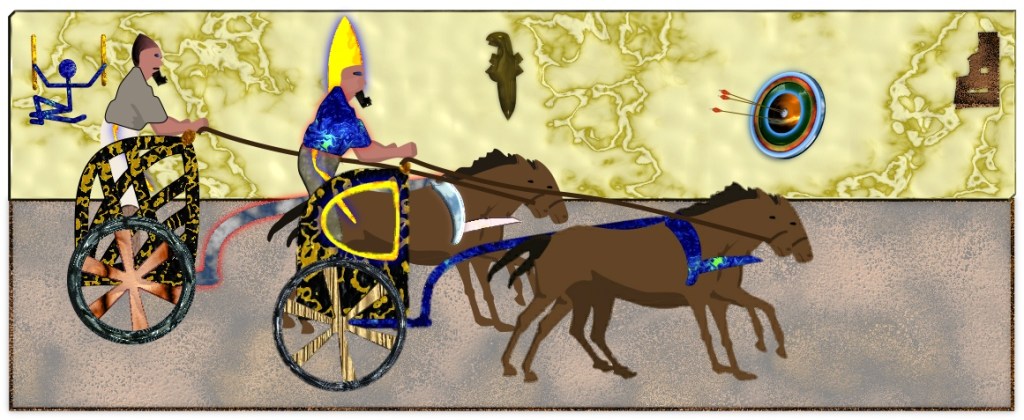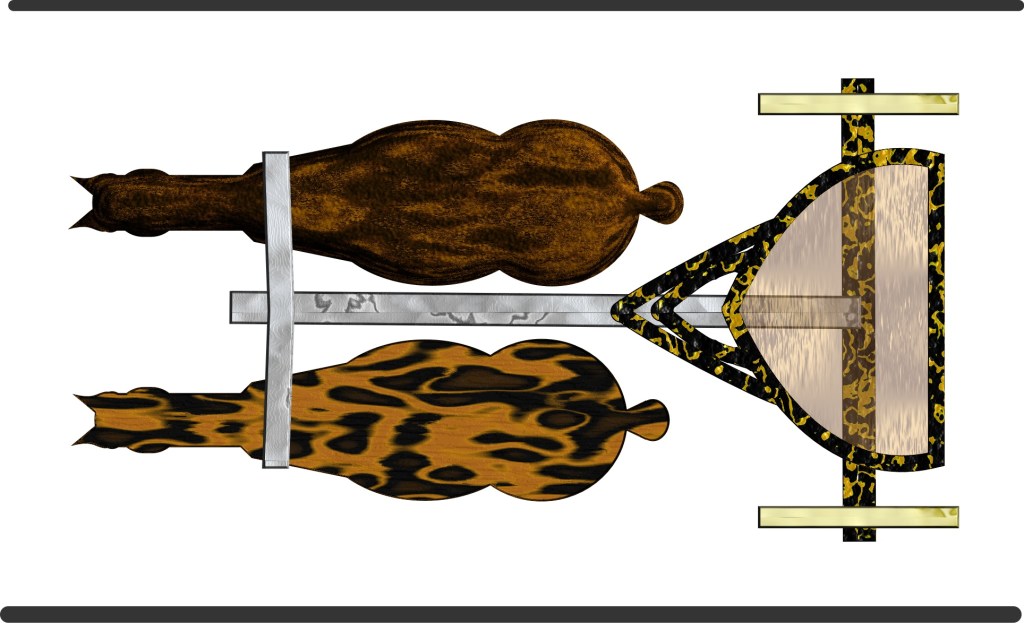
L’Étonnante Marelle Antique.
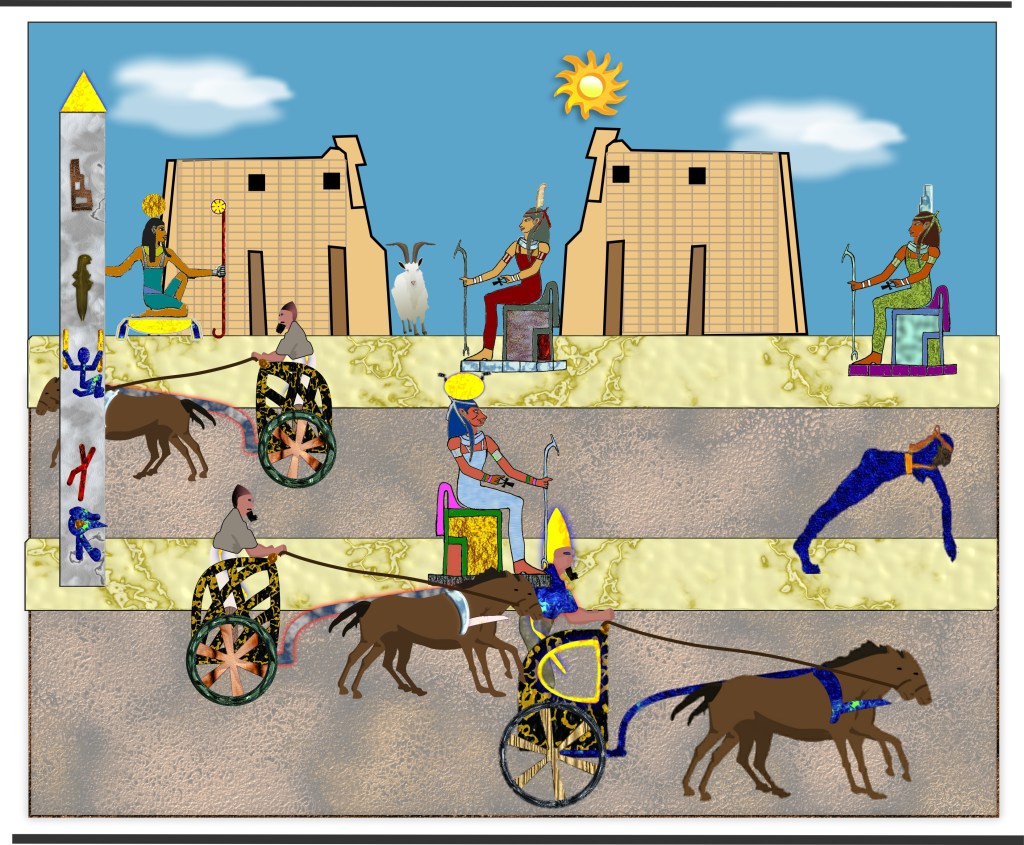
Une fois que l’on associe les signes hiéroglyphiques avec leurs propriétaires divins, il devient possible de les placer en fonction de ce que la marelle équestre nous propose.
Sa forme et ses dispositions prennent du sens car elle exprime clairement les croyances fondamentales Égyptienne, désigne ses personnages principaux et raconte aussi leurs rôles et interactions.
Sans marelle nous avons une simple liste de signes pratiques, avec elle nous avons un mode d’emploi et nous pouvons en admirer la cohérence. Encore plus étonnant, le manège équestre contemporain incorpore la quasi-totalité des ancêtres des lettres qu’utilisent quotidiennement des milliards d’humains.
Et il faut reconnaître qu’aucune autre explication de sa disposition ne répond totalement aux questions que nous nous posions au début de l’enquête.
La double finalité d’outil de formation et de lieu spirituel répond à la question de base : qu’est-ce que c’est ?
Ce n’est qu’un début. Le manège équestre Égyptien nous pose encore quelques questions : pourquoi l’avoir créé, qui l’a commis, quand le pensa-t-on et enfin où a-t-il été réalisé ?
Ce que nous recherchons, à défaut d’une nomenclature des constructions remarquables nous indiquant « ici l’on trouve le premier manège équestre de la nième dynastie », est un faisceau de présomptions mêlant les besoins, les capacités et les qualifications nécessaires, pendant une période de quelques centaines d’années.
C’est donc par une analyse des besoins que nous pouvons commencer, sachant que le manège est contemporain à l’introduction des chevaux en Égypte et forcément antérieur à la reconquête de l’ensemble de son territoire.
La Puissance du Sud.
Les suspects sont tout trouvés : comme créateurs d’une vaste école de cavalerie, les Antes, famille royale de la Haute-Égypte de l’époque dite du Nouvel Empire ont tout pour nous plaire.
Ils composent une lignée nombreuse, guerrière, volontaire et surtout Pharaonique. Historiquement, elle marque la fin de la 17e puis le commencement de la 18e dynastie suivant une continuité exceptionnelle, les changements de numérotation induisant normalement la disparition d’une famille au bénéfice de la suivante.
Ses personnages les plus éminents sont des Pharaons successifs : le grand-père Senakhtenrê Lâhmes, le père Seqenenrê Tâa et ses fils Khamôsis et Ahmôsis 1er, déjà cité comme étant le premier Pharaon « équestre » illustré.
A eux tous, ils forment la lignée des combattants ayant réuni la Haute et la Basse Égypte, en se battant longue-ment contre les Hyksôs, ces usurpateurs cavaliers qui s’étaient emparés de la Basse-Egypte près d’un siècle plus tôt.
Cependant, si ces rois sont importants, leurs reines le sont encore plus, qu’il s’agisse de la grand-mère Tétishéri, d’extraction de basse aristocratie, de sa fille Iahotep, qui épouse son frère Seqenenrê Tâa et de la petite fille Nefertary l’une des sœurs qu’épouse Ahmôsis.
Elles sont, chacune d’entre elles, extraordinaires de par leurs influences comme sœurs, épouses, régentes et souveraines successives.
Cela se remarque d’ailleurs dans les titres et honneurs qui leur sont attribués autant de leur vivant qu’après : reines, épouses royales, grandes épouses royales et enfin épouse de dieu , le grade le plus élevé à ce jour.
La grand-mère, la fille et la petite fille bénéficient de du-rées de vies bien plus longues que celle de leurs rois et époux. Ainsi, elles incarnent la continuité du plan d’unification de l’Égypte et de sa réussite, émaillée de nombreux drames et de quelques échecs.
Et surtout, du point de vue qui nous intéresse, elles sont sans aucun doute à la source, avec leurs Pharaons de ma-ris et de fils, du grand changement des armées du sud de l’Égypte : l’adoption de l’arme cavalière.
Ce qui nous ramène vers l’an -1650. Après l’installation de la 17e dynastie dont les premiers Pharaons, les prédécesseurs de Senakhtenrê Lâhmes et Tétishéri, se sont imposés par la force, la négociation ou la prévarication.
Ils ont su en finir avec le long émiettement de pouvoirs qui rendait leur région si faible. S’imposant aux autres grandes familles aristocratiques, ils recommencent, un demi-millénaire après les grandes pyramides, à construire en grand et à aménager de nouvelles cités, dont Ouasset qu’ils organisent en cour régionale.
Lorsque des groupes voisins ne se battent plus entre eux et que la prospérité revient, il faut trouver un objectif commun, aiguiser les appétits politiques et promettre de nouvelles richesses à répartir.
Batailleurs et conquérants, puissants et organisés, les Antes, unificateurs du Sud sont intéressés par ce qui laisse des traces, surtout si elles sont graphiques et à leur gloire.
La légende racontée par des kilomètres de hiéroglyphes chante les victoires de la lignée de Ahmôsis 1er. Ce qui nous enseigne deux choses :
• La première est connue. L’histoire est rédigée par les vainqueurs et à leur gloire, surtout si les vaincus ne savent pas écrire.
• La seconde, plus édifiante est que la culture équestre d’importation fera florès dans les écuries des Pharaons et sur tous les supports de présentation de leur puissance guerrière.